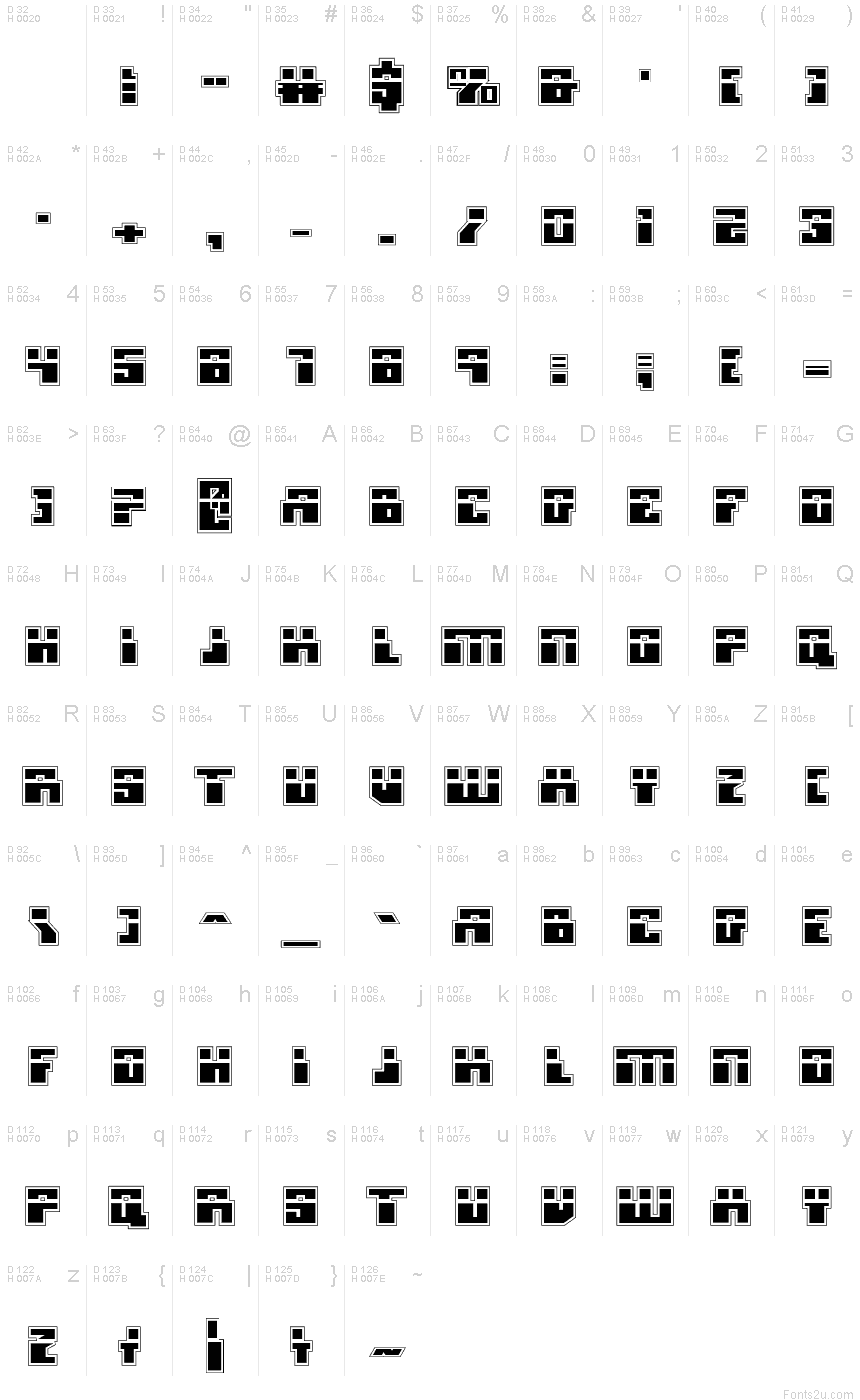
Micronian Laser Academy, entworfen von Iconian Fonts, ist eine kostenlose Techno-Display-Schrift aus breiten, quadratischen Formen. Ihre Buchstaben nutzen abgestufte Ecken, rechteckige Ausschnitte und eingelegte Linien, die an Paneele eines Arcade-Automaten oder einer Science-Fiction-Konsole erinnern.
Sie fügt sich mühelos in eine fiktive Steuerungsoberfläche ein. Dieselbe strenge Geometrie eignet sich für Spieltitel, Event-Plakate, Esports-Branding und Merchandise für elektronische Musik, insbesondere bei industriellen oder bildschirmbasierten Themen. Schaltpläne, Statusleisten und mechanische Illustrationen können ihre rechteckigen Lücken und internen Linien aufgreifen, sodass die Beschriftung wie ein gestaltetes Maschinenteil wirkt.